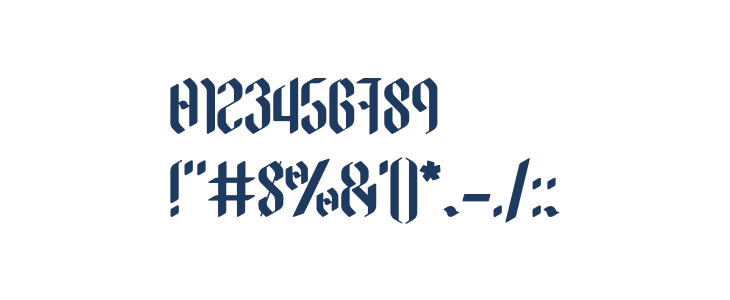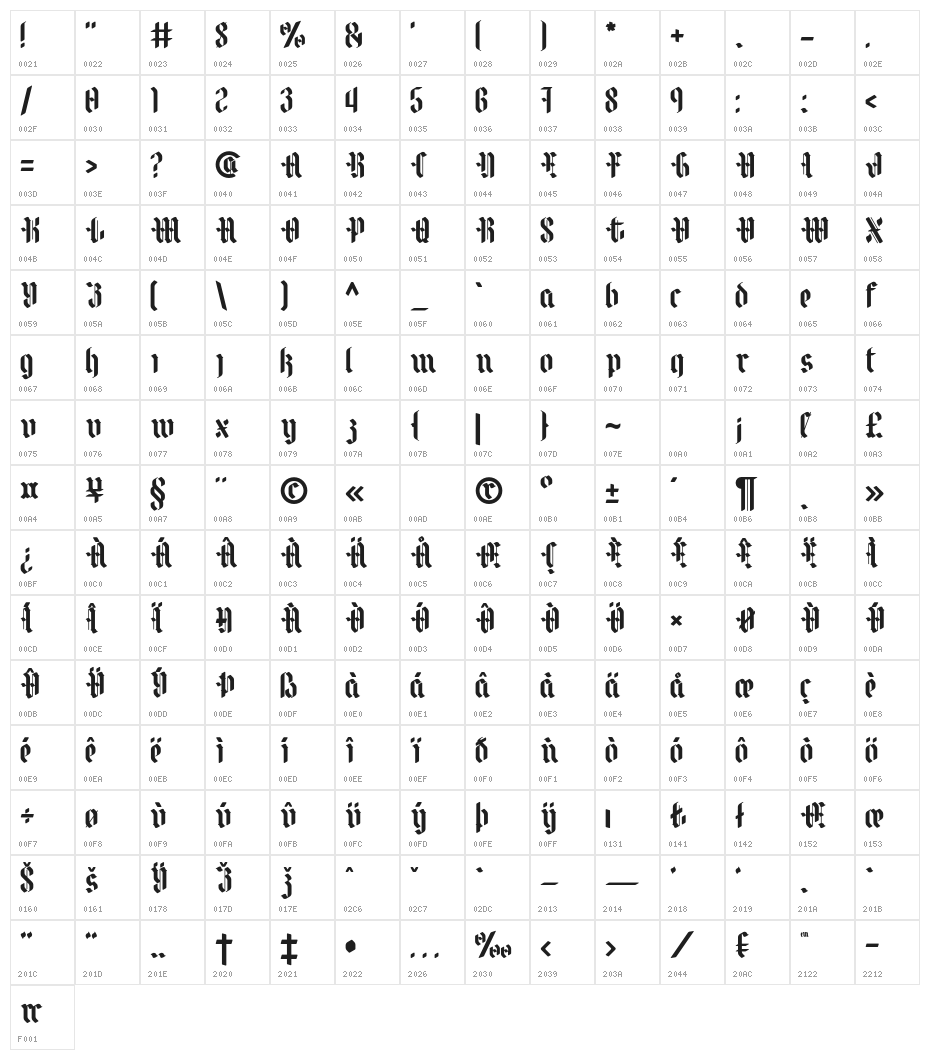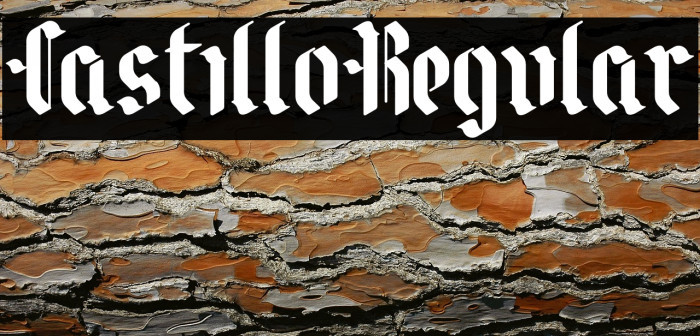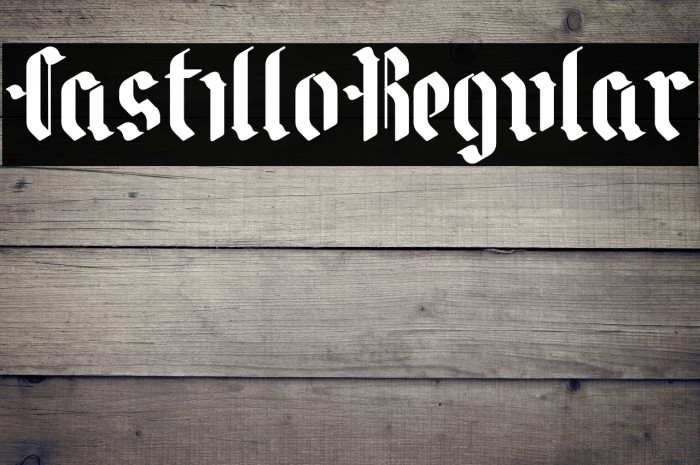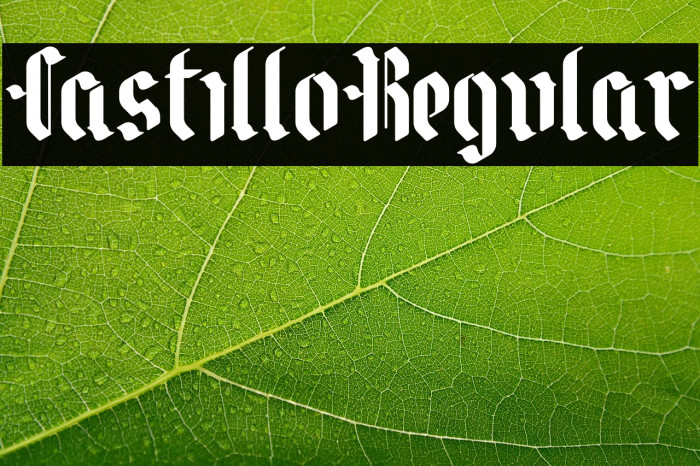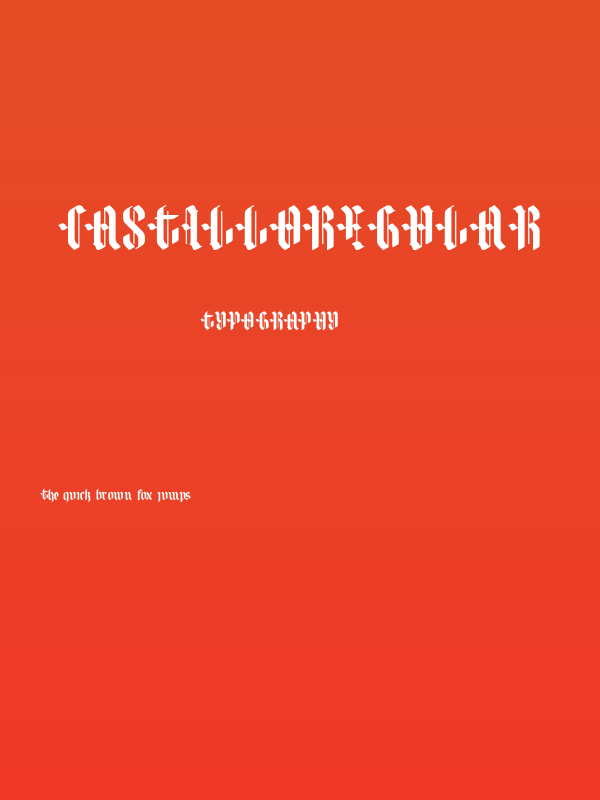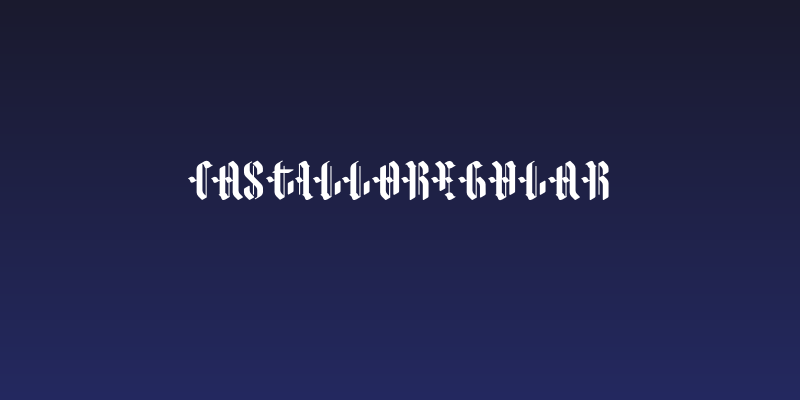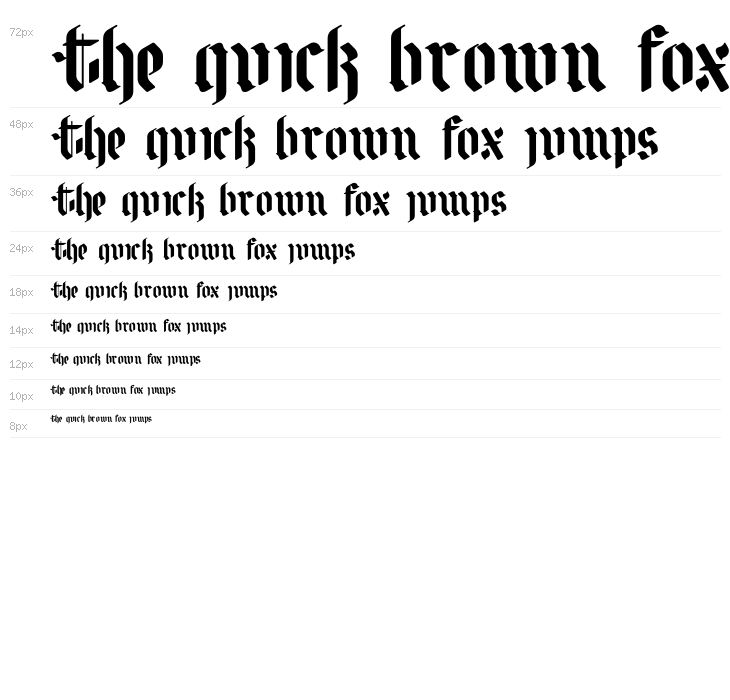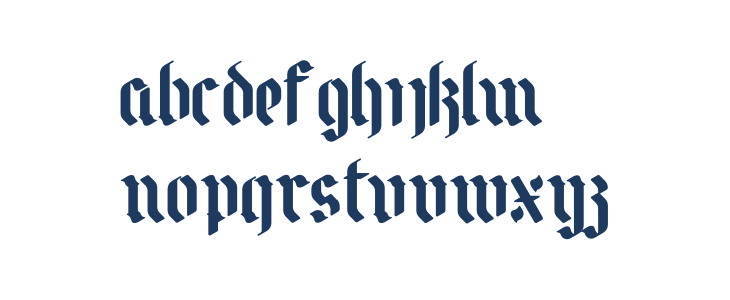
CastilloRegular Font
| Caso d'uso | Logos, Headlines, Decorative text |
| Progetti proposti | Suitable for historical documents, medieval-themed designs, book covers, and branding that requires a traditional or authoritative look. |